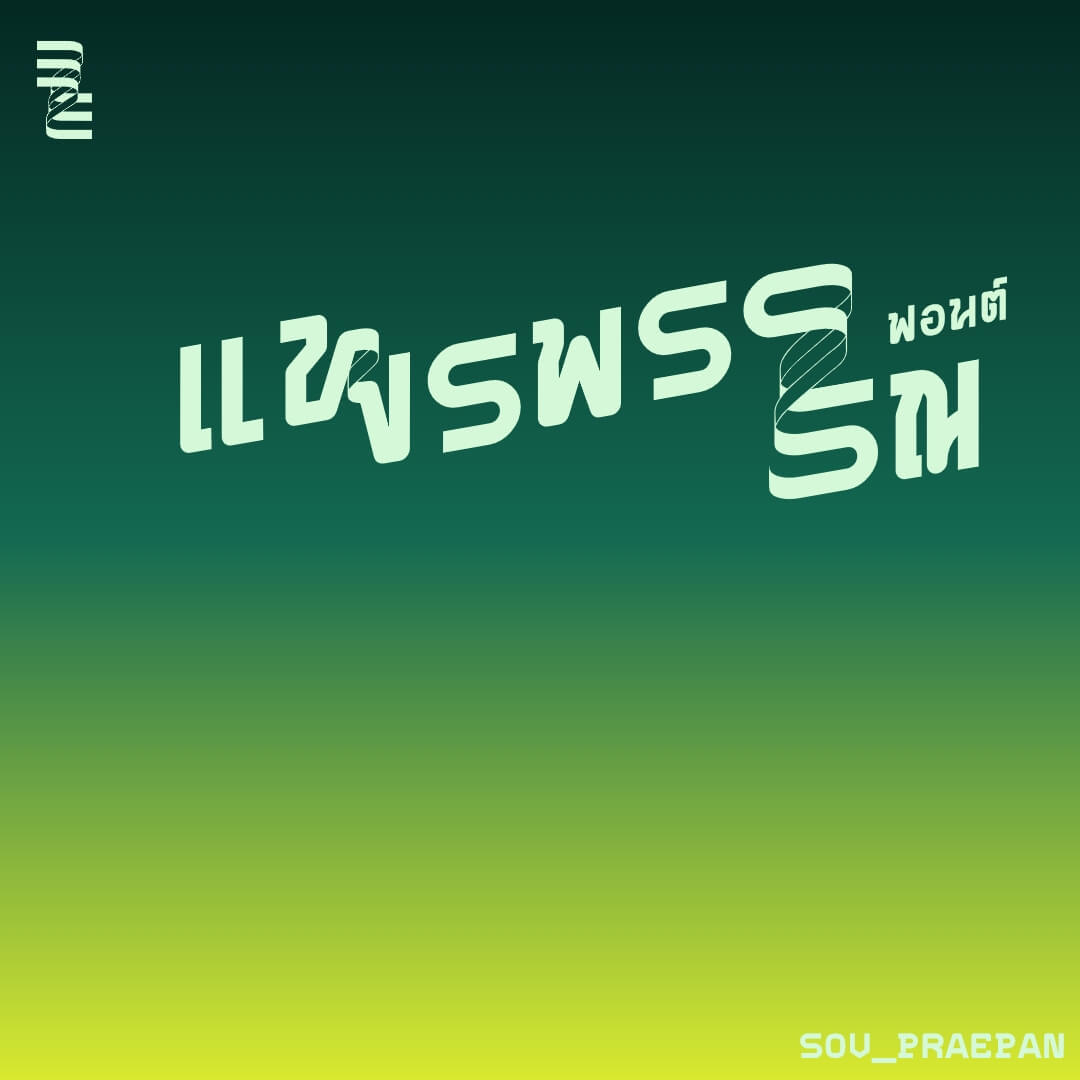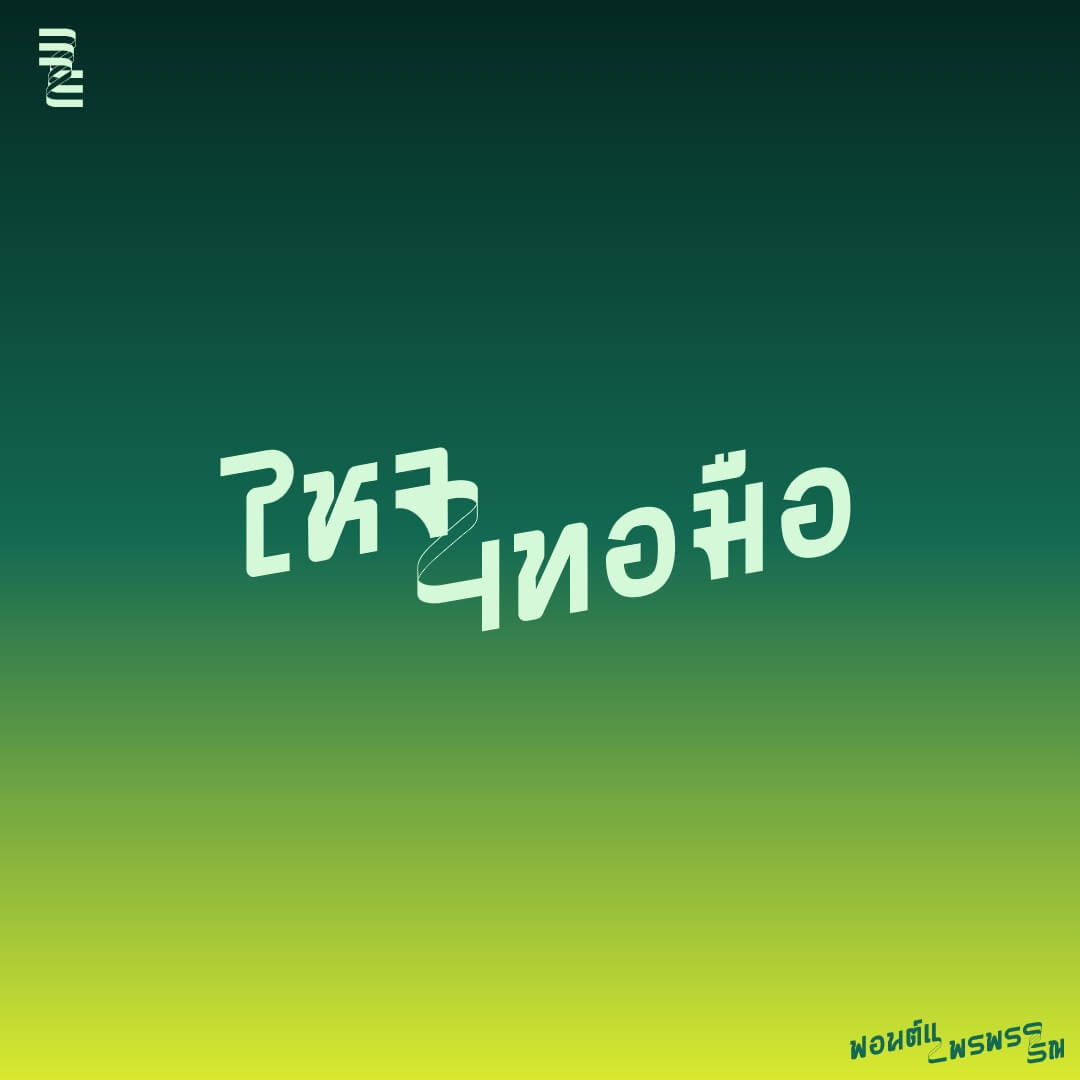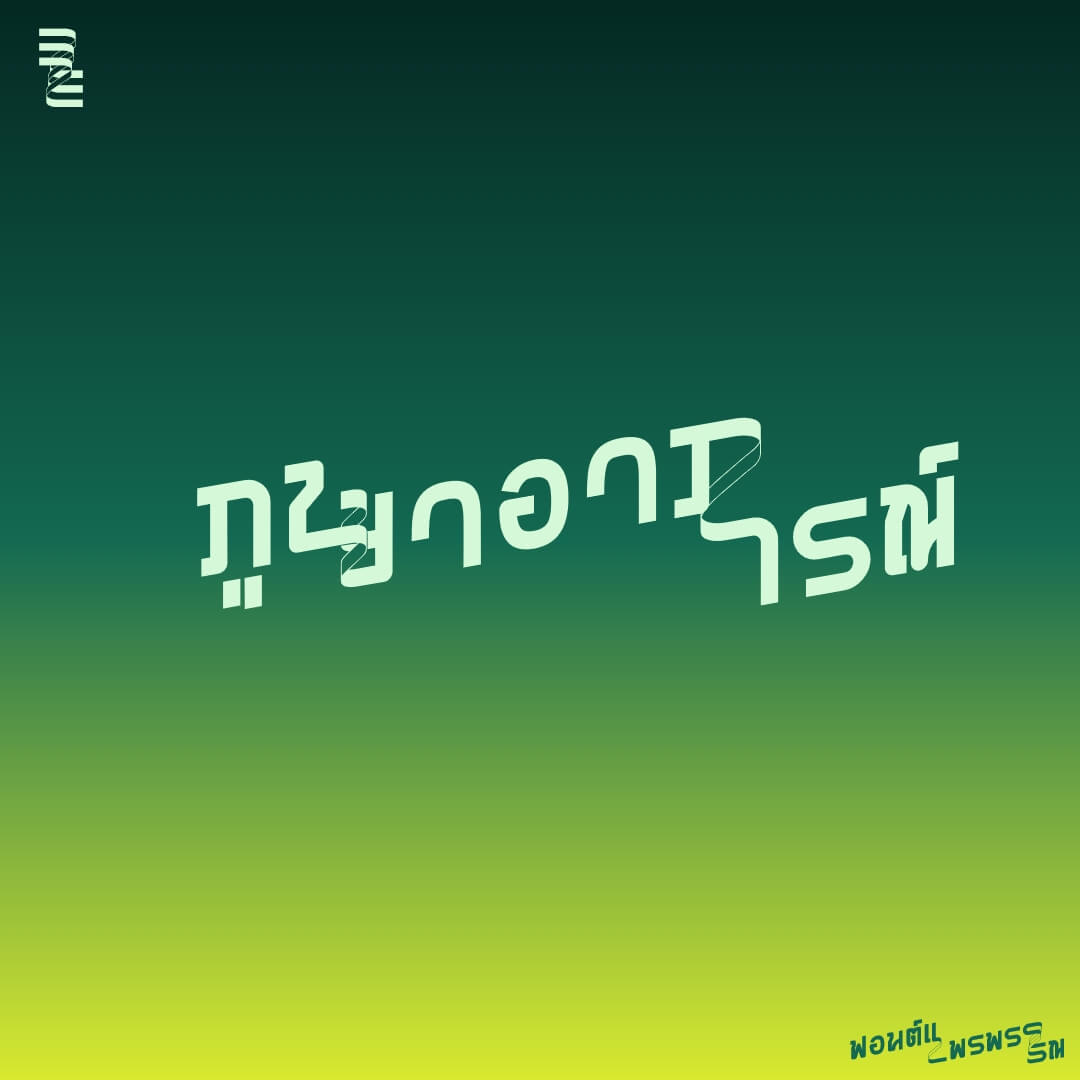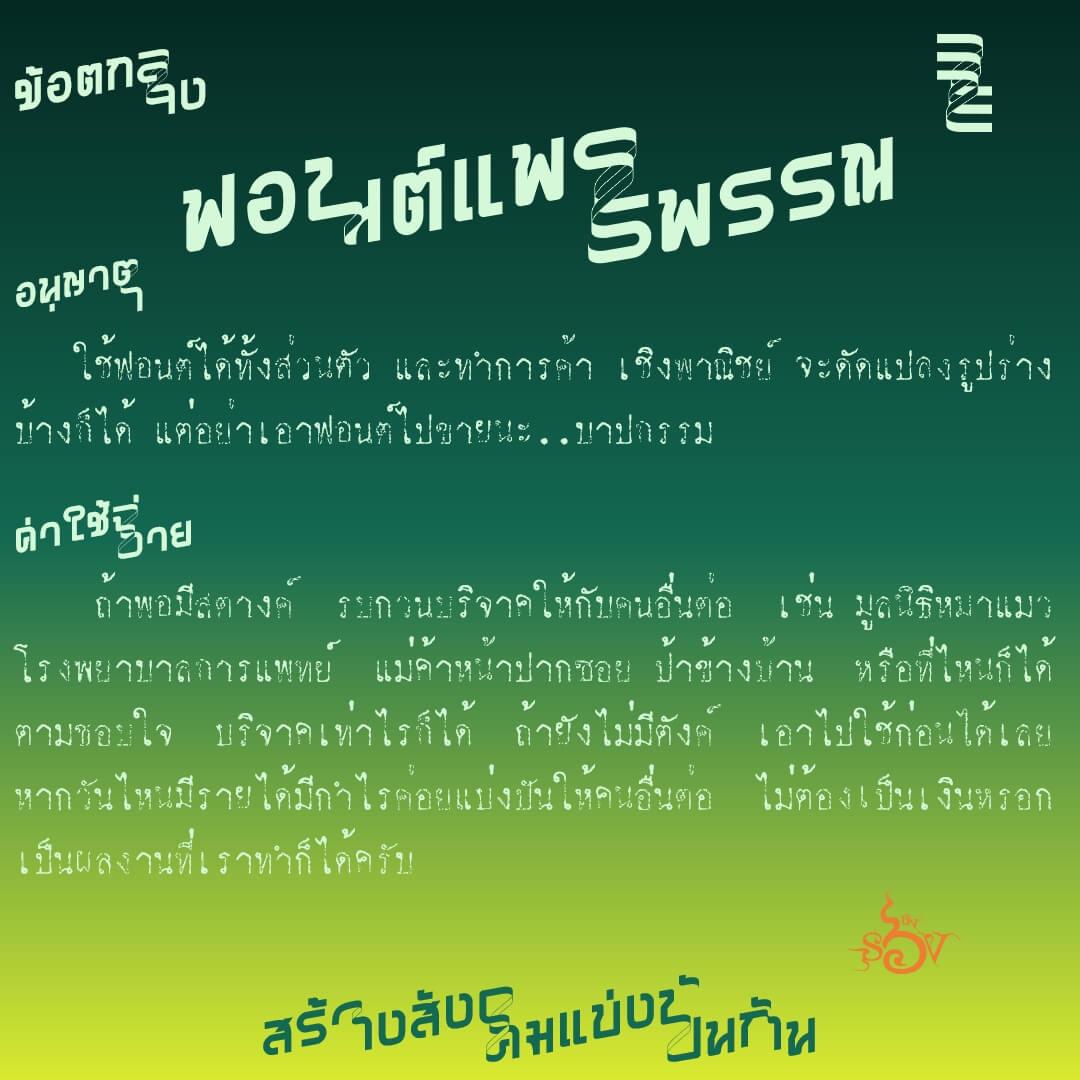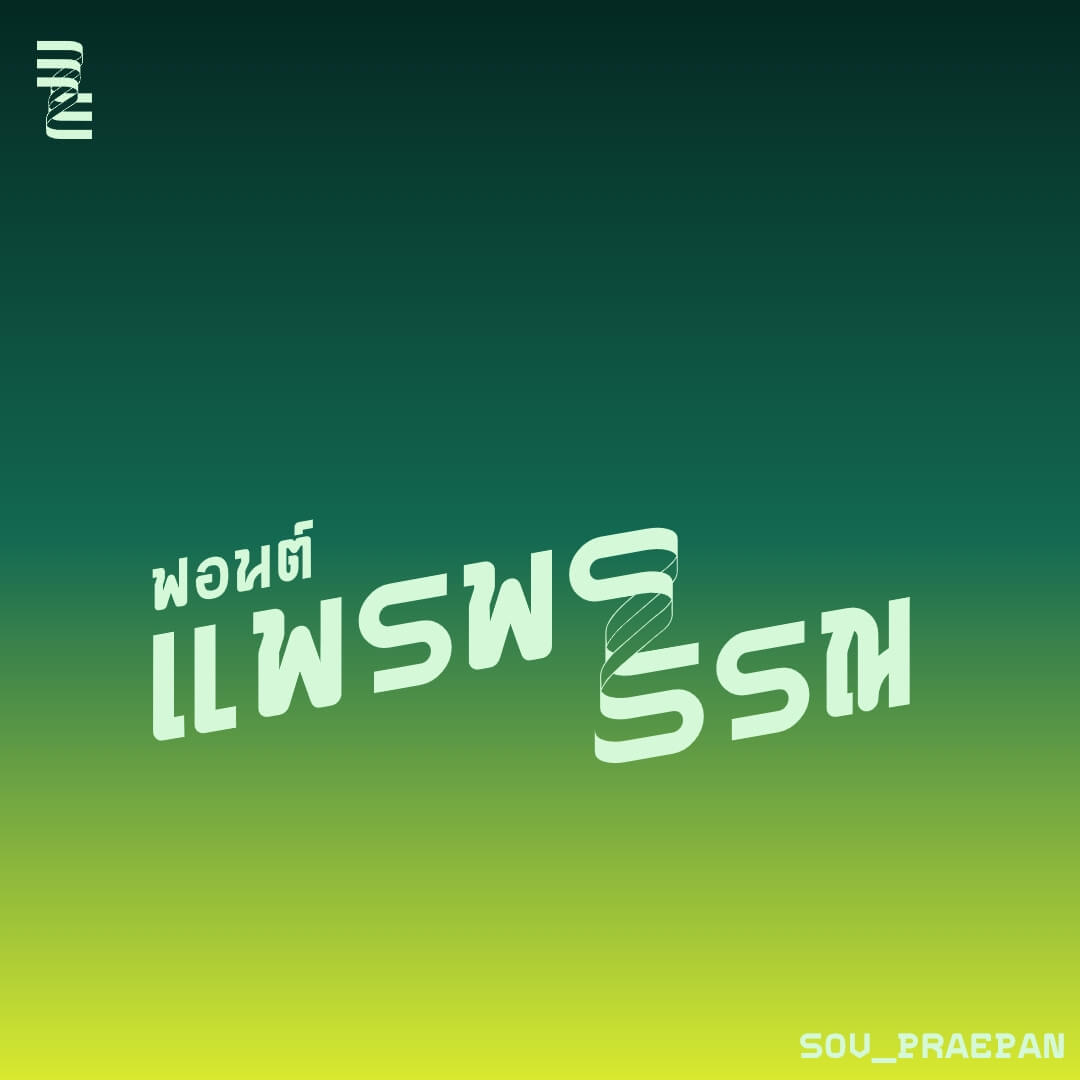
แพรพรรณ (SOV_PraePan)
ฟอนต์แพรพรรณ – เป็นฟอนต์ริบบิ้นอีกแบบหนึ่ง อาจเรียกว่าเป็นธง เป็นผืนผ้า น่าจะเหมาะกว่า ใช้เป็น logo font … แต่จะใช้กับประโยคก็ได้ ยังไงก็สะดุดรอยพับอยู่แล้ว